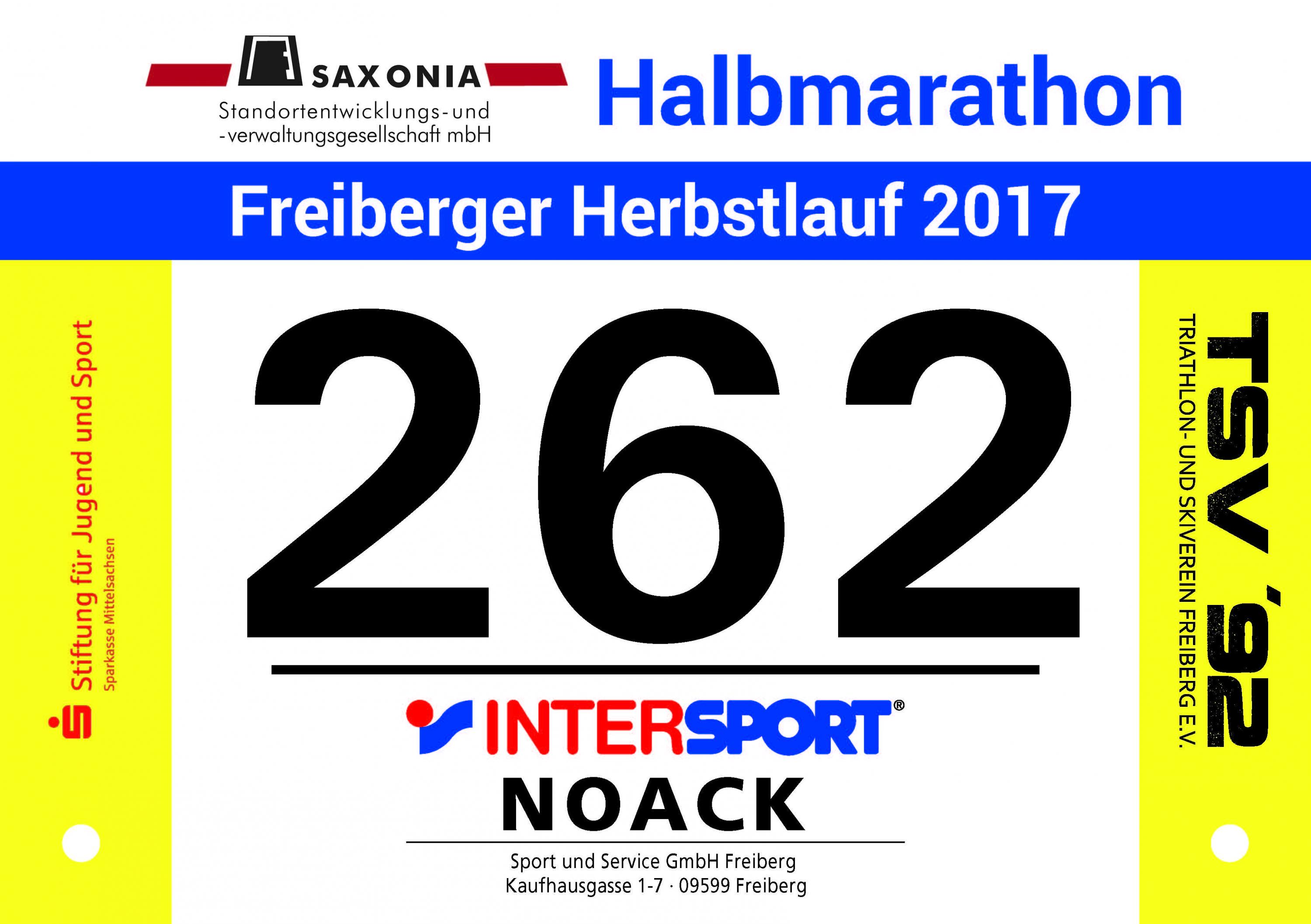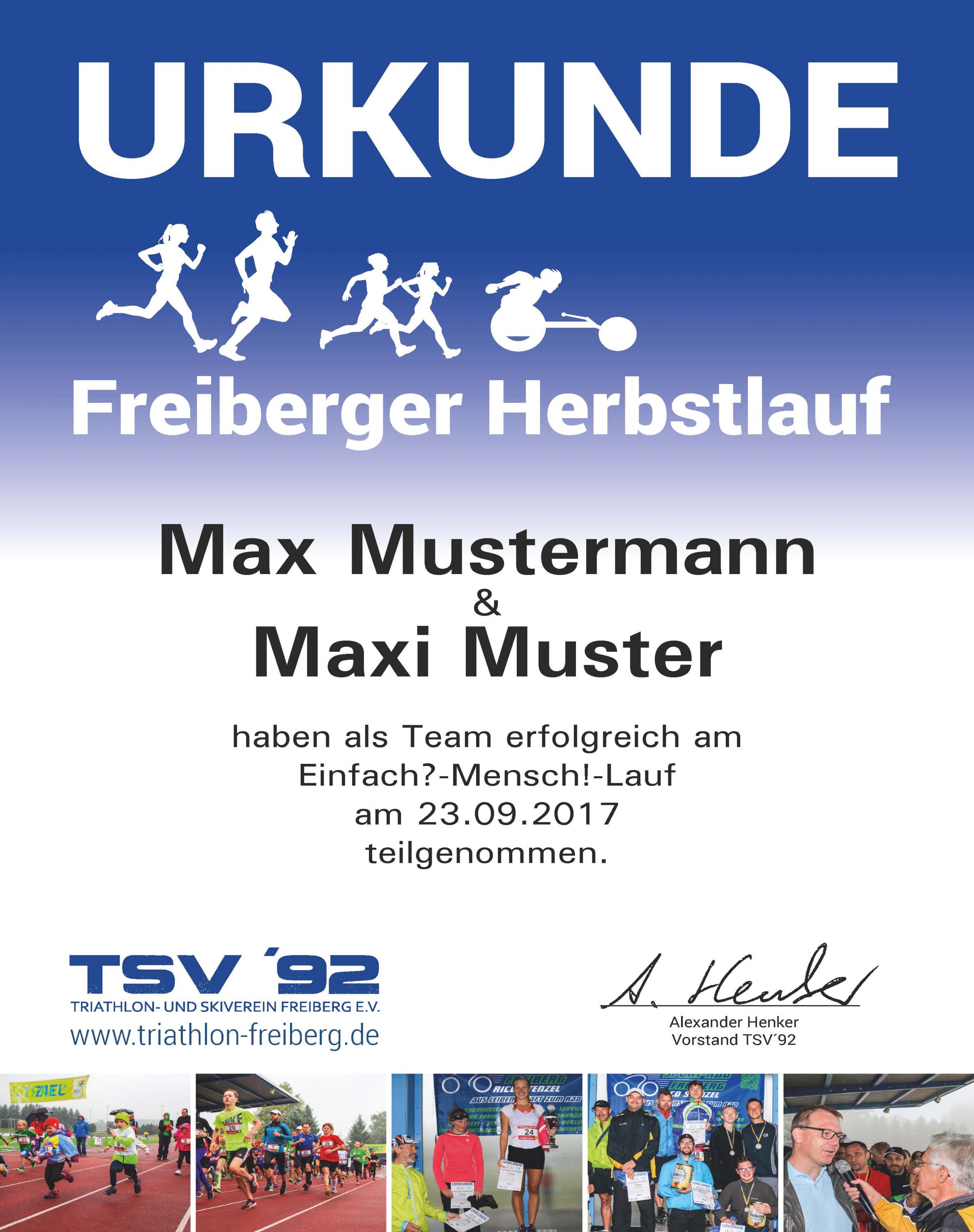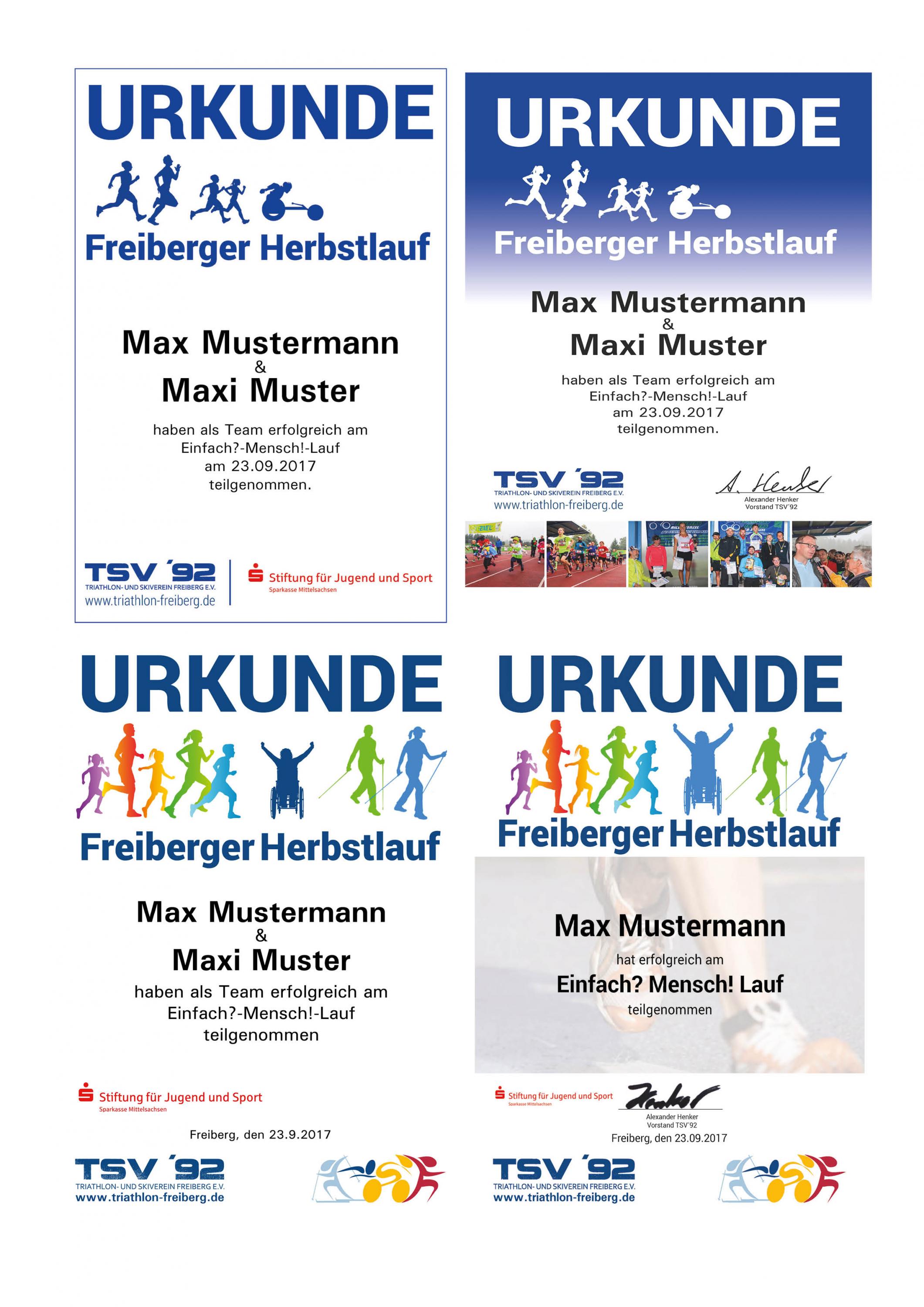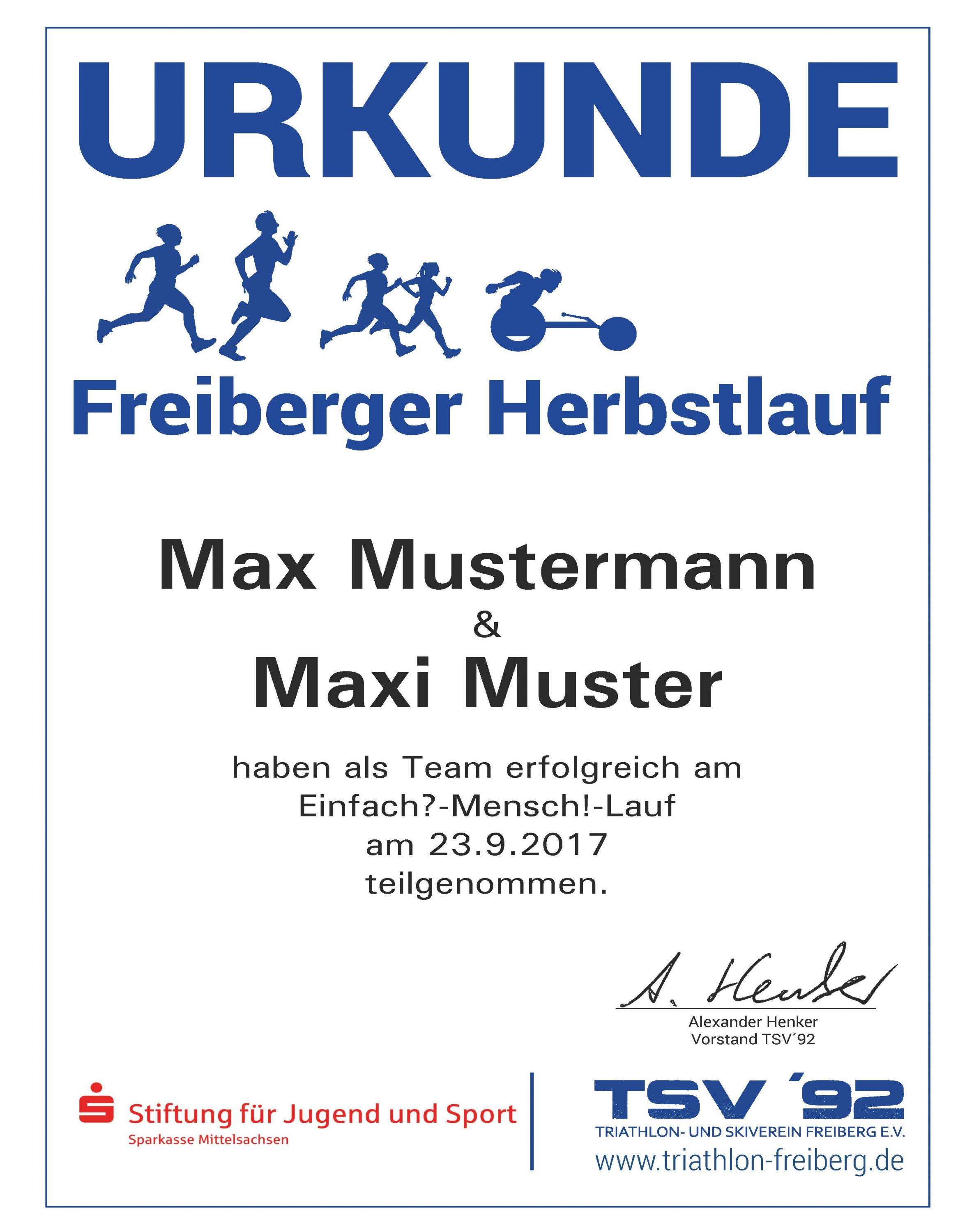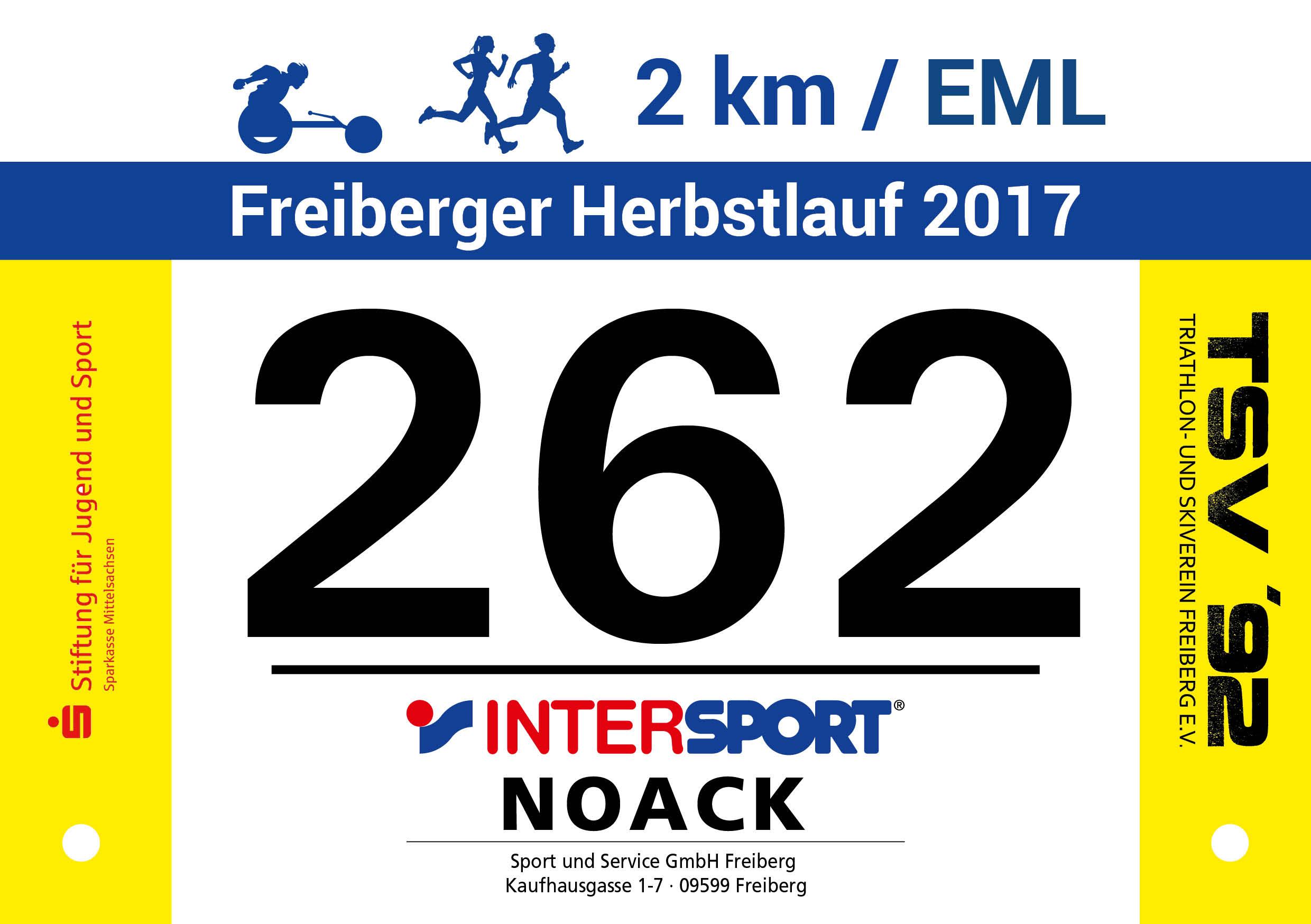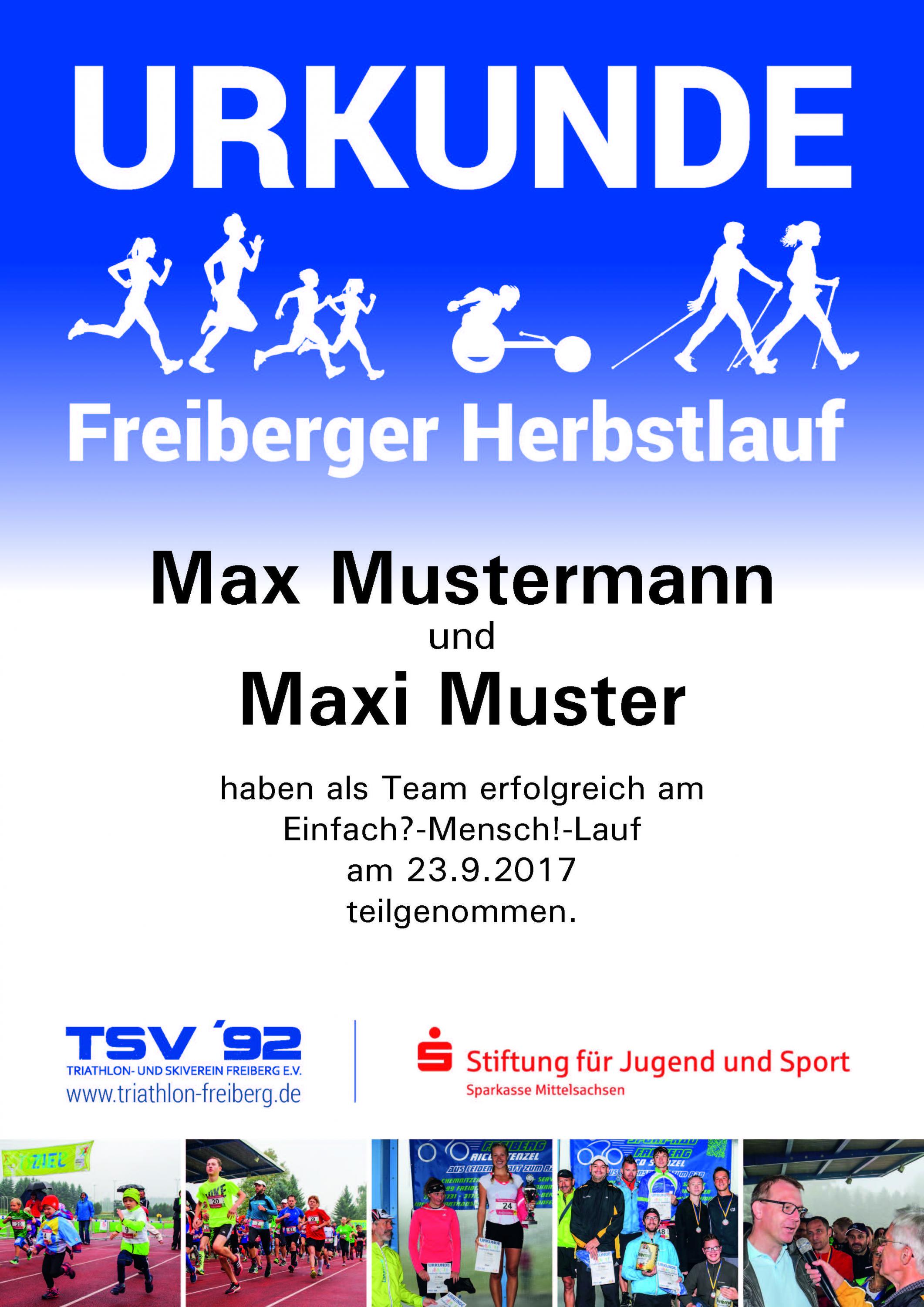
Schrift für Urkunde - Laufveranstaltung
Roboto
es war die Roboto
Wow! Das war nicht mal Absicht! :-D
Ich habe einfach nach einer Sans-Serif-Schrift gesucht in meiner Font-Sammlung, die nicht Arial heißt, und bin dann eben auf die Roboto gestoßen, die ich übrigens sehr häufig verwende.
So, ich habe mal die Ideen aufgegriffen und noch ein paar eigene eingebaut :-)  Die Nordic-Walker fehlen noch aber so in die Richtung kann ich es mir gut vorstellen. Habe jetzt überall die Roboto (Startnummern und Urkunde) und auch einheitlich das Blau aus dem Vereinslogo.
Ich hätte mich am Entwurf von Designfreak orientiert, mehr sage ich zu Deiner neuen Urkunde jetzt mal nicht. Und was die Startnummer angeht: Mir ist das viele Drumherum zu groß und lenkt von der Nummer ab, die ja eigentlich das Wichtigste sein sollte.
Ich hätte mich am Entwurf von Designfreak orientiert, mehr sage ich zu Deiner neuen Urkunde jetzt mal nicht.
Kein Kommentar ist auch ein Kommentar und so nehme ich das mal als Kritik an und gehe noch mal in mich. Sollte auch kein Aufwand weiter sein aber ich dachte halt es ist den Versuch noch mal wert und fand auch das Ergebnis gelungen. Offenbar eine Fehleinschätzung :-)
Und was die Startnummer angeht: Mir ist das viele Drumherum zu groß und lenkt von der Nummer ab, die ja eigentlich das Wichtigste sein sollte.
Die Nummer muss gut von weiten Erkennbar sein und ja, darum geht es. Ich finde aber das ist so auch gegeben und der Rest ist auch nicht ganz unwichtig. Der Sponsor oben zahlt etwas für den Laufnamen "Saxonia-Halbmarathon", Intersport zahlt die gesamten Startnummern, die Sparkassenstiftung gibt etwas für die Zeiterfassung dazu  und wir, der TSV sind die Ausrichter des Laufs.
Bin eben noch mal in meinen Ordner mit den Startnummern der Läufe bei denen ich so schon gestartet bin und da gefallen mir die mit etwas Drumherum besser als die mit nur der Zahl auf der Nummer.
Haben jetzt links oben die Anregung von Designfreak aufgegriffen ...
… die mir nach wie vor mit Abstand am besten gefällt. Jetzt muss nur noch die Reihe der Läufer rechts um die Nordic-Walker ergänzt, die führende Null im Datum beseitigt, das &-Zeichen mit etwas mehr Luft nach oben und unten versehen, das Sparkassen-Logo anders platziert und die Unterschrift des Vereinsvorsitzenden (eine Urkunde ist doch normalerweise immer unterschrieben) ergänzt werden und die Sache ist fertig.
und die Unterschrift des Vereinsvorsitzenden (eine Urkunde ist doch normalerweise immer unterschrieben) ergänzt werden
"Ob da die Unterschrift des TSV-Vorstands auch noch sein muss? Wohl eher nicht, aber wenn doch, dann auf keinen Fall so weit vom Logo entfernt."  :-)
Beide Antworten sind von Dir ...  Ich denke es muss nicht sein und ist ja mehr ein gestalterisches Element. Also mal sehen wo ich die noch platzieren kann und ob das dann passt ..
Ich bin ja sonst auch eigentlich Fan des & (und kein sturer Anhänger der Auffassung, es nur für Firmennamen zu verwenden), aber hier stört es mich schon. Konkret habe ich Probleme damit, den Satz als solchen wahrzunehmen. Ich vermute, dass ein ausgeschriebenes und die Sache erleichtern würde. Und dann sollten sie Zeilenabstände zwischen Max …, und, Maxi … sowie haben … wohl alle (optisch) gleich groß erscheinen.
Wir mussten uns entscheiden und haben uns entschieden :-) Die Variante mit den Fotos hat am besten gefallen und so haben wir die jetzt auch bestellt. Bei den Medaillen ging es nicht ohne den goldenen Rand (im nächten Jahr gibt es dann eine geprägte Variante ohne Vorgaben und Beschränkungen).
Die Medaille ..
die Startnummern:
die Urkunden: